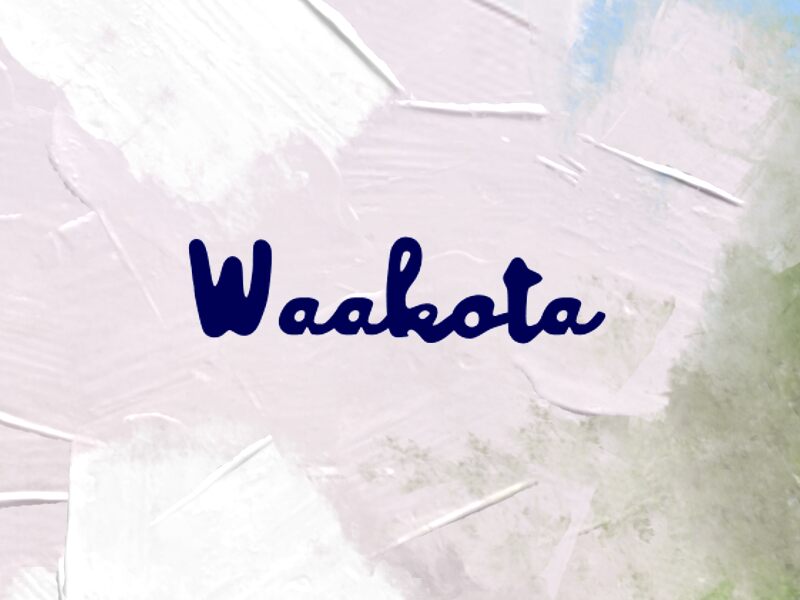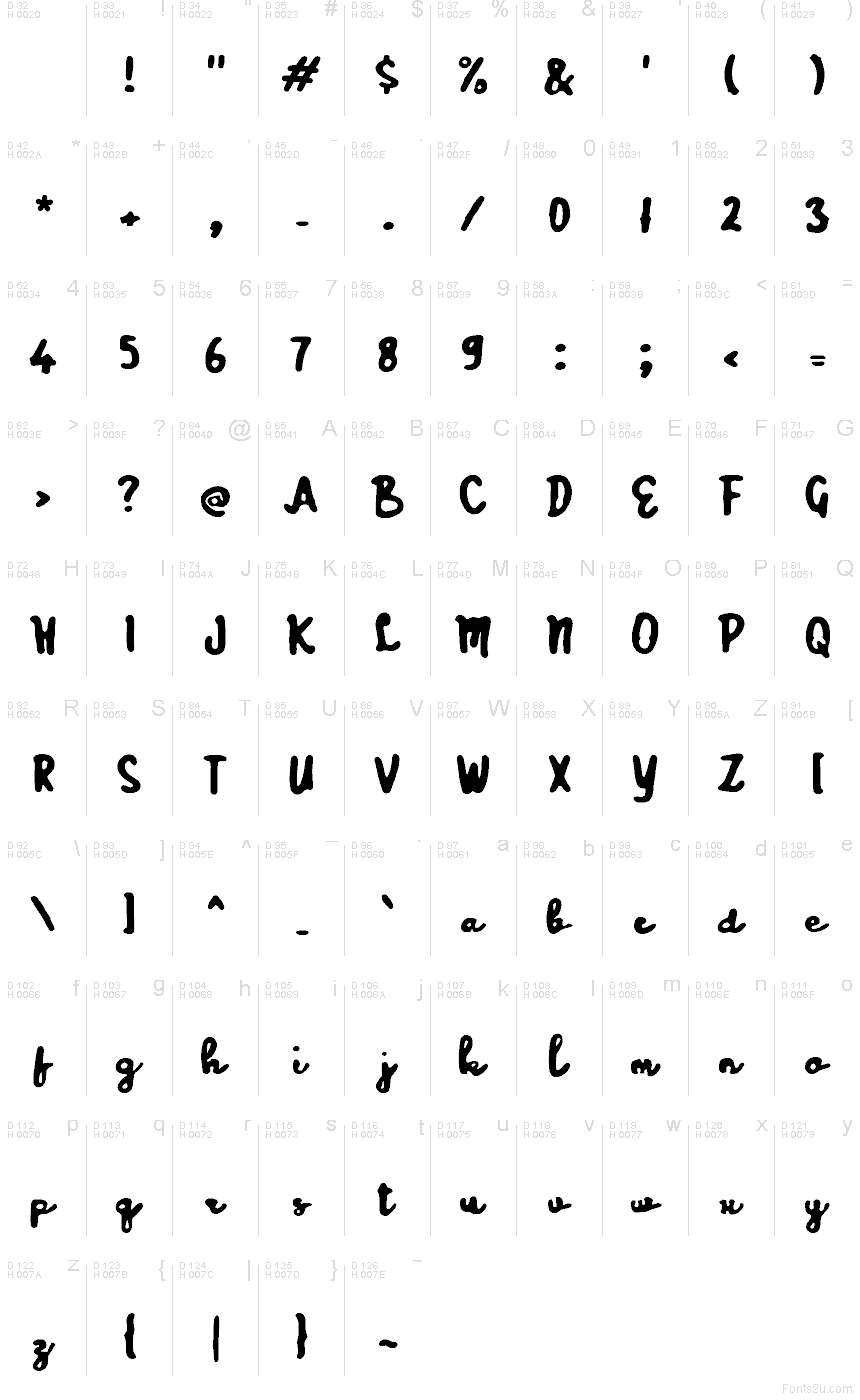
Waakota от Wep - это бесплатный шрифт в стиле brush, основанный на неспешном, волнообразном ритме и широких округлых штрихах: буквы кажутся скорее отлитыми, чем написанными. Связные формы остаются мягкими и компактными, а пухлые изгибы и короткие петли придают шрифту плотный, дружелюбный характер, в отличие от быстрых каллиграфических начертаний.
Такой уверенный flow отлично смотрится в логотипах кафе, на упаковках снеков, стикерах, обложках альбомов и заголовках в соцсетях, где нужно, чтобы рукописная форма обладала реальным весом. Короткие фразы работают лучше всего, так как мягкие соединения и глубокая темная текстура превращают простые слова в самостоятельный графический элемент.
Waakota
Презентация и наглядный образец шрифта Waakota